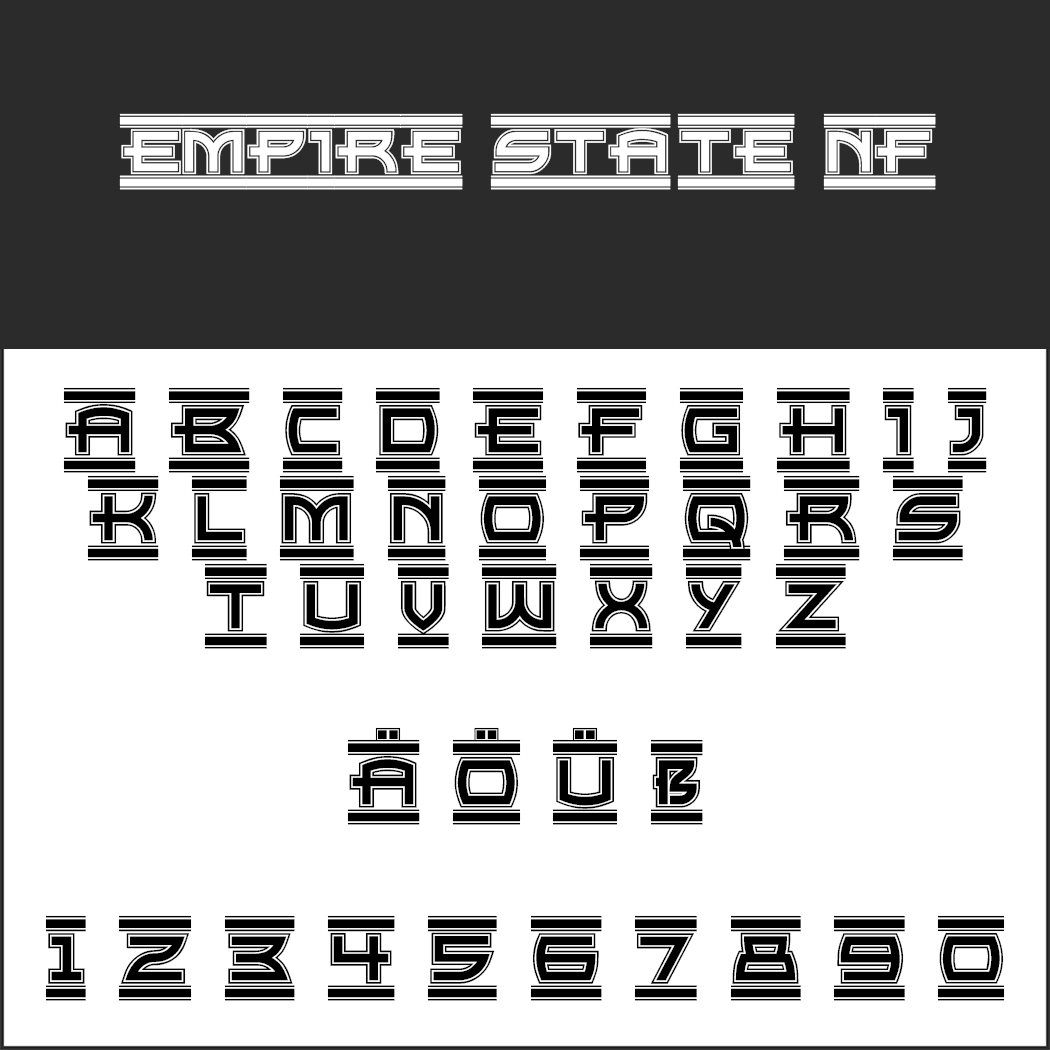
Ob Datum, Preis oder wiederkehrende Texte – mit einem Stempel kann man diese Informationen schnell, einfach und leserlich aufs Papier bringen. Eine echte Arbeitserleichterung eben. Denn ein Stempel bringt Vieles kurz und knapp auf den Punkt. Deshalb kommt auch eine Schriftart Stempel bei knackigen Aussagen und Hinweisen zum Einsatz.
Die verfügbaren Gratis-Fonts zum Herunterladen, die auch kommerziell genutzt werden dürfen, bestechen überwiegend durch gewollte Unregelmäßigkeiten. Genau das verleiht ihnen den Eindruck, dass die abgebildeten Wörter wirklich gestempelt wurden.
Schriftart Stempel – gratis kommerziell nutzbar
Stempel Schriftart "CODE ZLYHANIA"Code Zlyhania
Der ungarische Font vermittelt den Eindruck des vielgenutzten Stempels. Eine gute Wahl bei kurzen Schlagwörtern in Versalien.
Schrift "ED GEIN"Ed_Gein
Die Buchstaben und Zahlen stehen auf skizzierten Notizblöcken, die mit ihren Spiralen für einen zusätzlichen Hingucker sorgen. Die Versalien des zweiten Satzes sind etwas niedriger, so dass sie als Kleinbuchstaben genutzt werden können. Als Umlaut gibt es nur das Ö, was wohl der ungarischen Herkunft geschuldet ist.
Stempel Schrift "Empire State NF"Empire State NF
Der Font ist von einer Briefmarkenausgabe der United States Postal Service von 1999 inspiriert. Für den Stempelcharakter der akuraten Buchstaben und Zahlen sorgen lediglich die oberen und unteren Balken.
Schrift "HVD Bodedo"HVD Bodedo
Für diesen Font haben die Berliner Designer Bodoni-Buchstaben aus Kartoffeln geschnitzt. Der authentische Look kommt also nicht von ungefähr. Inklusive Kleinbuchstaben und deutschen Sonderzeichen bietet HVD Bodeo viele Einsatzmöglichkeiten.
Stempel Schriftart "HVD Poster"HVD Poster
Ebenfalls handgemacht aus der Berliner Typoschmiede HVD, aber ohne Serifen. Die kleineren Buchstaben sind hier auch Versalien, die sich im Aussehen leicht von den größeren unterscheiden.
Stempel Schrift "JADEFEDGA"Jadefedga
Wie nachlässig ausgeschnittene Kartoffeldruck-Buchstaben präsentiert sich der Font des finnischen Designers. Die Größe der einzelnen Zeichen variiert daher sehr stark, was kurzen Schlagwörtern einen eigenwilligen Charme verleiht.
Schriftart "Kingthings Printingkit"Kingthings Printingkit
Der englische Designer lässt mit diesem Font eine Kindheitserinnerung wieder aufleben: das John Bull Printing Outfit. Dabei handelt es sich um ein Stempelset, mit dem Kinder Wörter und Zahlen in Plastikschienen stecken können. Nutzt man diesen selbstgemachten Stempel, drucken sich ungewollt auch Teile dieser Schienen ab – genau so wie sie hier im Font zu sehen sind.
Schrift "OFFSHORE BANKING BUSINESS"Offshore Banking Business
Eine Kombination aus Stempel- und Schablonenschrift präsentiert der Designer mit Offshore Banking Buisness, die sich nur für kurze Schlagwörter eignet – oder Texte, die als bekannt vorausgesetzt werden dürfen. Denn die Lesbarkeit ist stark eingeschränkt.
Stempel Schrift "OLD STAMPER"Old Stamper
Der Name sagt im Prinzip bereits alles: Old Stamper ist einem alten Stempel nachempfunden. Die Leisten, in die die Buchstaben gesteckt wurden, erscheinen unten und oben als durchgehende Linien in dem ungarischen Font.
Schriftart "VTC Fuzzy Punky Slippers"VTC Fuzzy Punky Slippers
Weder die Buchstaben noch die Umrandungen sind bei VTC Fuzzy Punky Slippers besonders akkurat. Damit drückt der Font kaum Seriosität, aber um so mehr gepflegte Lässigkeit aus.
Stempel Schriftart ZERO & ZERO ISZero & Zero Is
Dieser „Stempel“ hat die besten Zeiten hinter sich: die Buchstaben ausgefranst, die Ränder immer deutlich mit abgedruckt. Der Font passt für Nostalgisches und Geheimnisvolles. Die beiden Versalien-Sätze unterscheiden sich in Größe und Details.